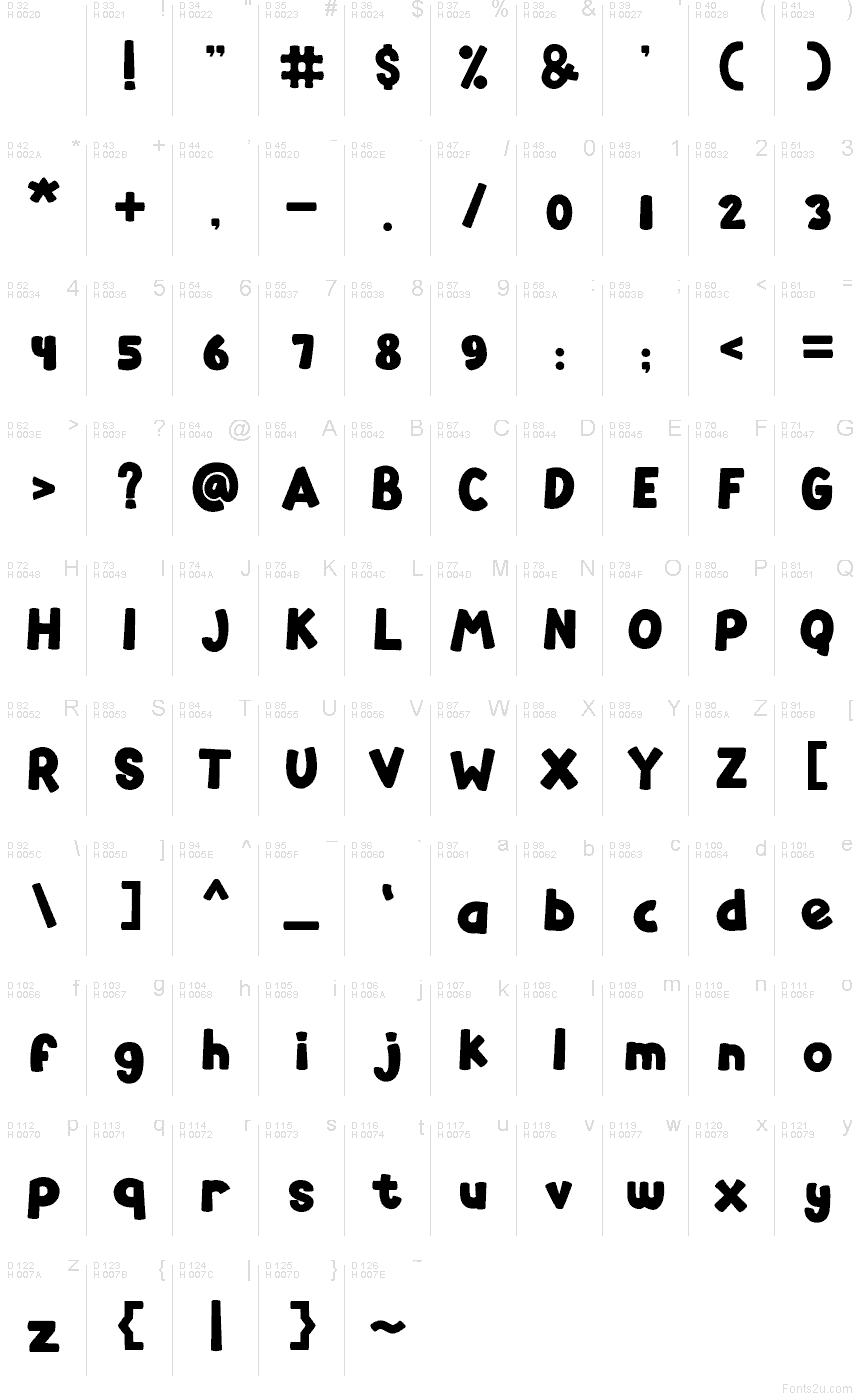
Cherioz od Tokokoo je bezplatné kreslené písmo s oblými tvary znaků a jemným, ručně řezaným rytmem. Působí kompaktně a přátelsky, má plynulé křivky, úzké otevřené části a lehce nerovnoměrné zakončení, které mu dodává uvolněný, pohádkový nádech.
Cherioz skvěle vynikne na dětských obalech, v komiksových nadpisech, na plakátech, v logotypech, u nápisů v kavárnách nebo v krátké grafice na sociální sítě. Díky zaobleným tvarům si zachovává čitelnost i v úderných textech. Tento bezplatný font vnese lehký ilustrativní nádech do každého projektu, který vyžaduje veselý vzhled bez zbytečného formalismu nebo přehnaného vyhlazení.